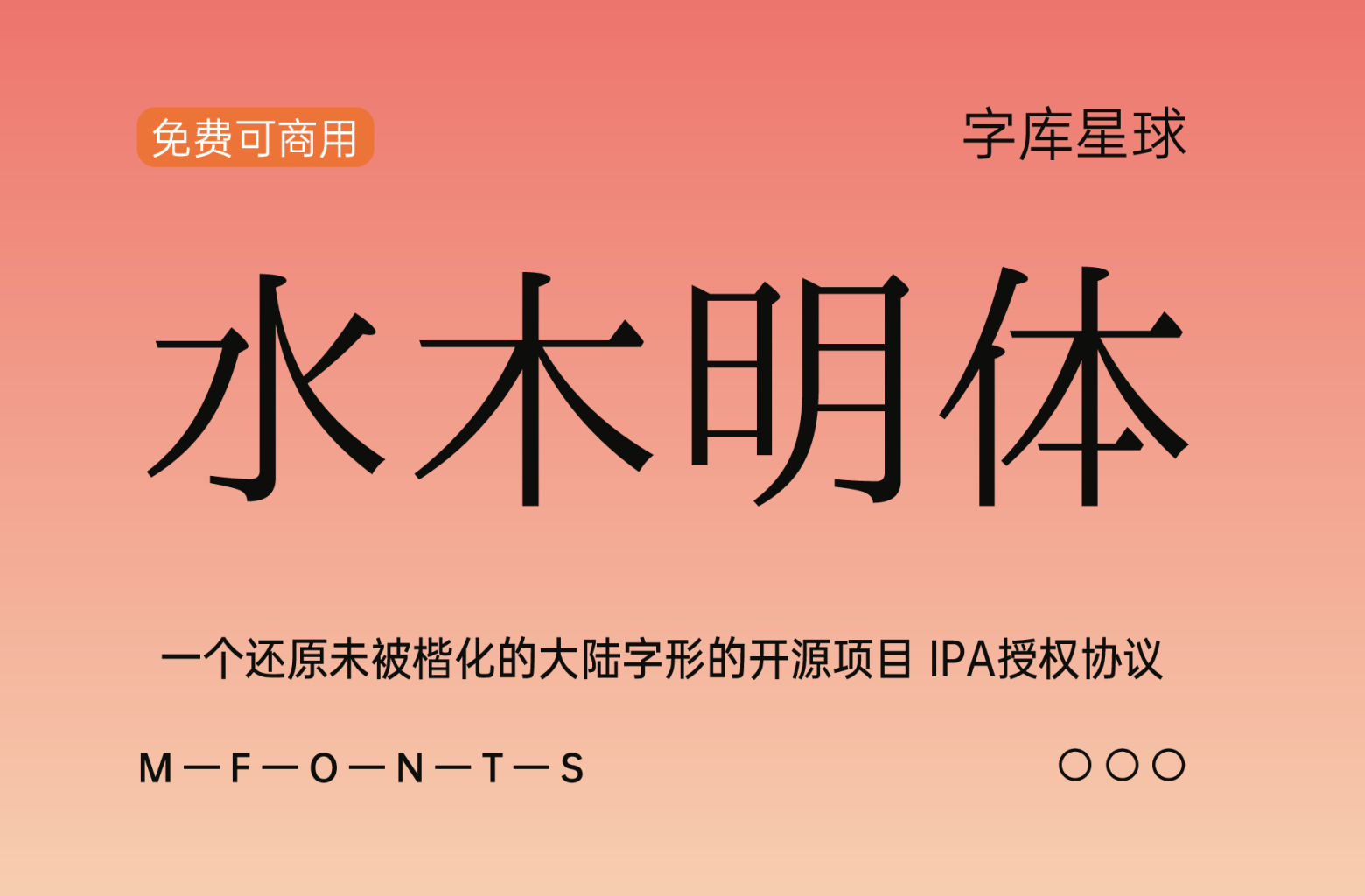
2009 年,日本「独立行政法人情报处理推进机构」(IPA)将「IPA 明朝」和「IPA ゴシック」两款字型按照 IPA Font License 开源发布。这两款字型分别衍生自 TypeBank 公司出品的、由林隆男(Takao Hayashi)设计的「TB 明朝」和「TB ゴシック」。后经多年持续修订,两款字型扩充成「IPAex 明朝」「IPAex ゴシック」,包含 JIS 第一~第四水准的字符。而「IPAmj 明朝」是对「IPAex 明朝」的进一步扩充,包含了「文字情报基盘」所涵盖的汉字及其诸多 IVD 变体。
本项目「水木明体」为「IPAex 明朝」「霞鹜致宋」的衍生字形,在原有的字形基础上,将笔画和写法调整为中国大陆地区规范,但保留印刷体特征,如断笔、八屋根、挑捺(饰笔)等,将大陆宋体中的楷化部分去除,给您一个纯粹的印刷字体!
2023 年中,「水木明体」项目创建,以一点明体为基础,将字形改为大陆地区规范,并保留了印刷体特征。后来由于草字头汉字过多,便一直搁置,始终得不到完善。直至2024年2月中,我的电脑被砸毁,导致字体制作无法进行,五月十日,购入新电脑,便继续字体制作,制作速度也快多了。由于时间流逝,多种旧字形宋体一一涌现,其中便包括「霞鹜致宋」,我便以其CL版本基础上重制,舍弃原本使用一点明体的文件,并补充了一部分霞鹜致宋缺少的字。本项目致力于复原未被楷化的印刷体风格的字形。
收字情况
首次发布的「霞鹜致宋」收录「国际表意文字核心」(IICore)范围内的 9810 个汉字。
何为 IICore?
「国际表意文字核心」(International Ideographs Core,IICore)是 CJK 统一表意文字编码的最小子集,包含了两岸四地、日本、南韩、北朝鲜等区域提交的总共 9810 个常用汉字,可用於记忆体容量和输入/输出资源有限的设备,以及/或那些不能使用整套 ISO/IEC 10646 表意文字字集的应用系统。IICore 包含 9706 个基本区汉字、42 个扩展 A 区汉字和 62 个扩展 B 区汉字,於 2003 年 IRG 第 21 次会议提出,2004 年 IRG 第 22 次会议通过。
目前「霞鹜致宋」包含 IICore 所收录的 9810 个常用汉字,以及原始授权字型「IPAex 明朝」所包含的 JIS 第 1~4 级别汉字,和「jf 7000 当务字集」基本包所收字。而水木明体在此基础上,补充了一些雅名用字、补齐了元素周期表。
- 为拉丁字母增加连写:ffi, fi, fl, ffl, fj, ffj, Th, st, St, ff, fh(需要开启自由连写)